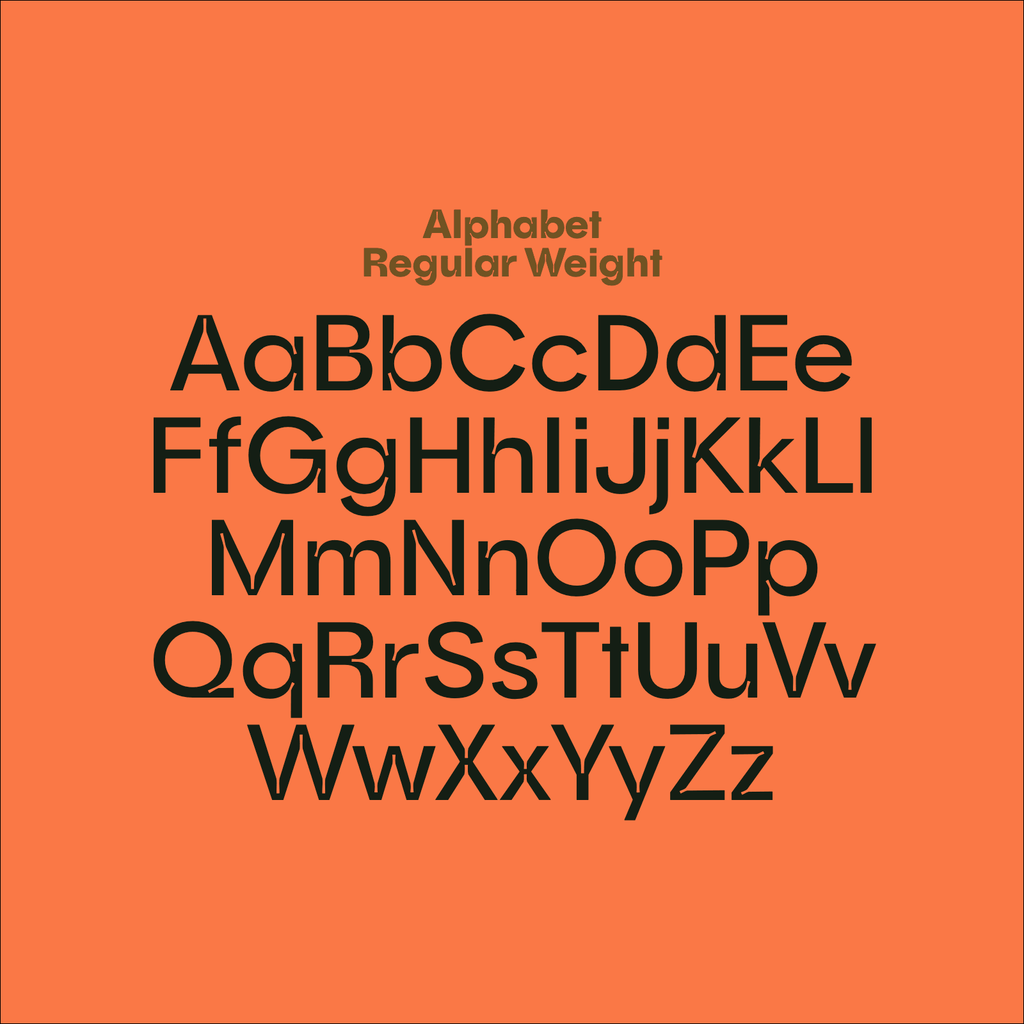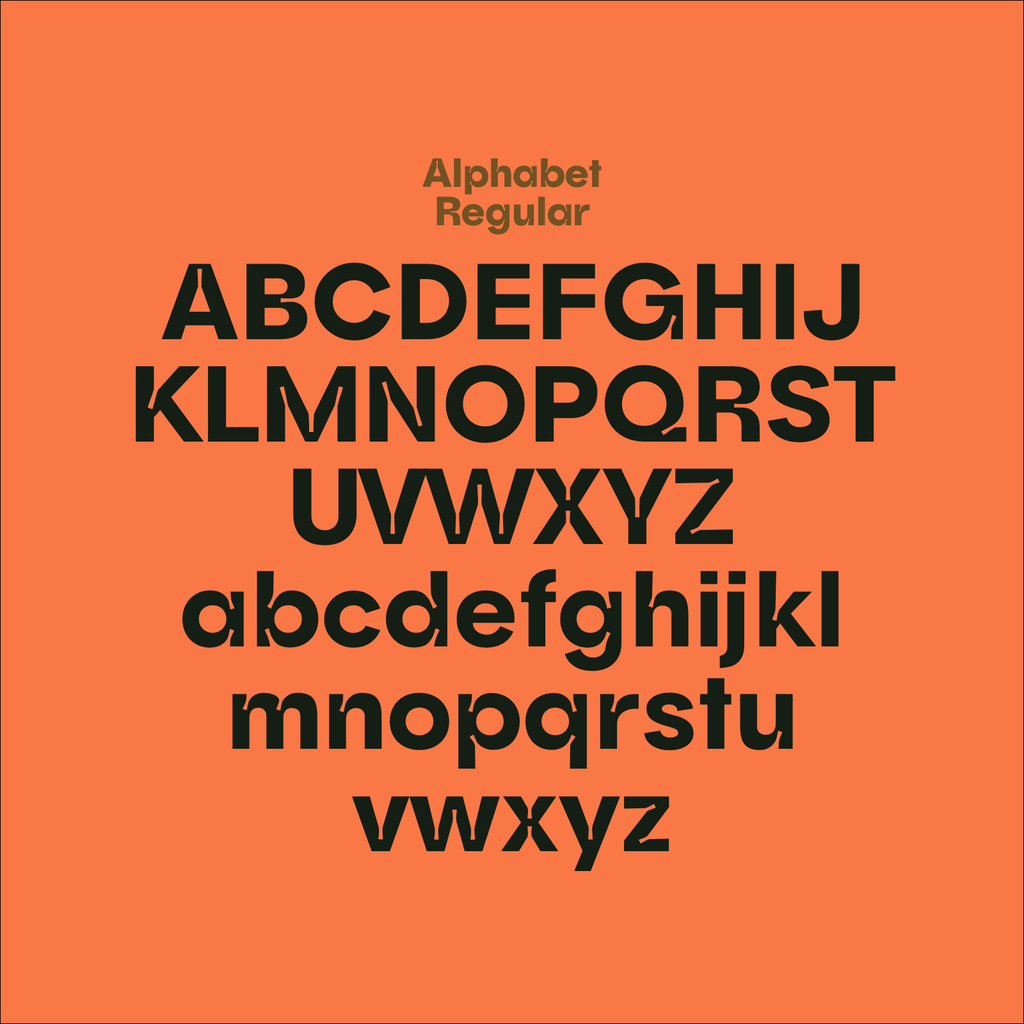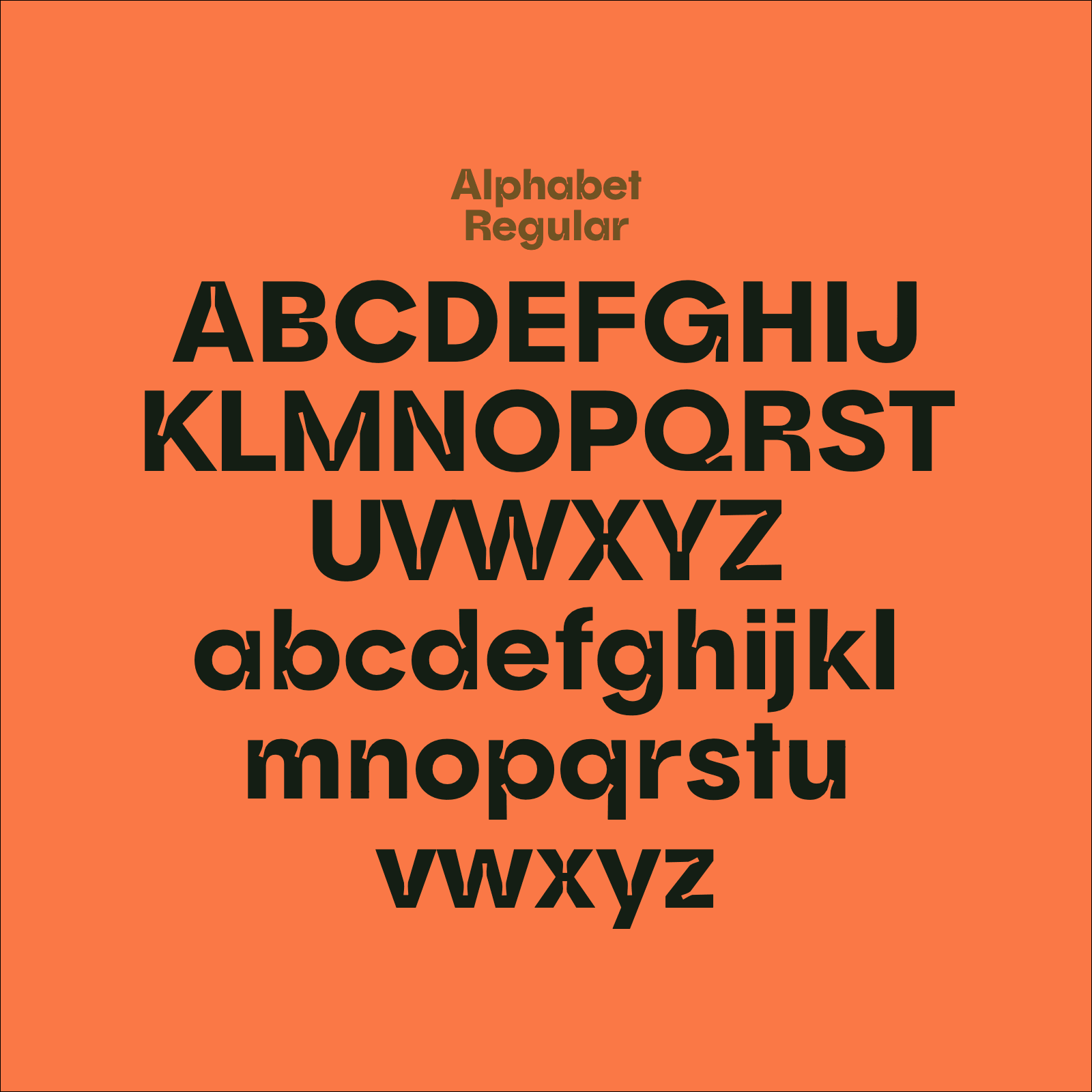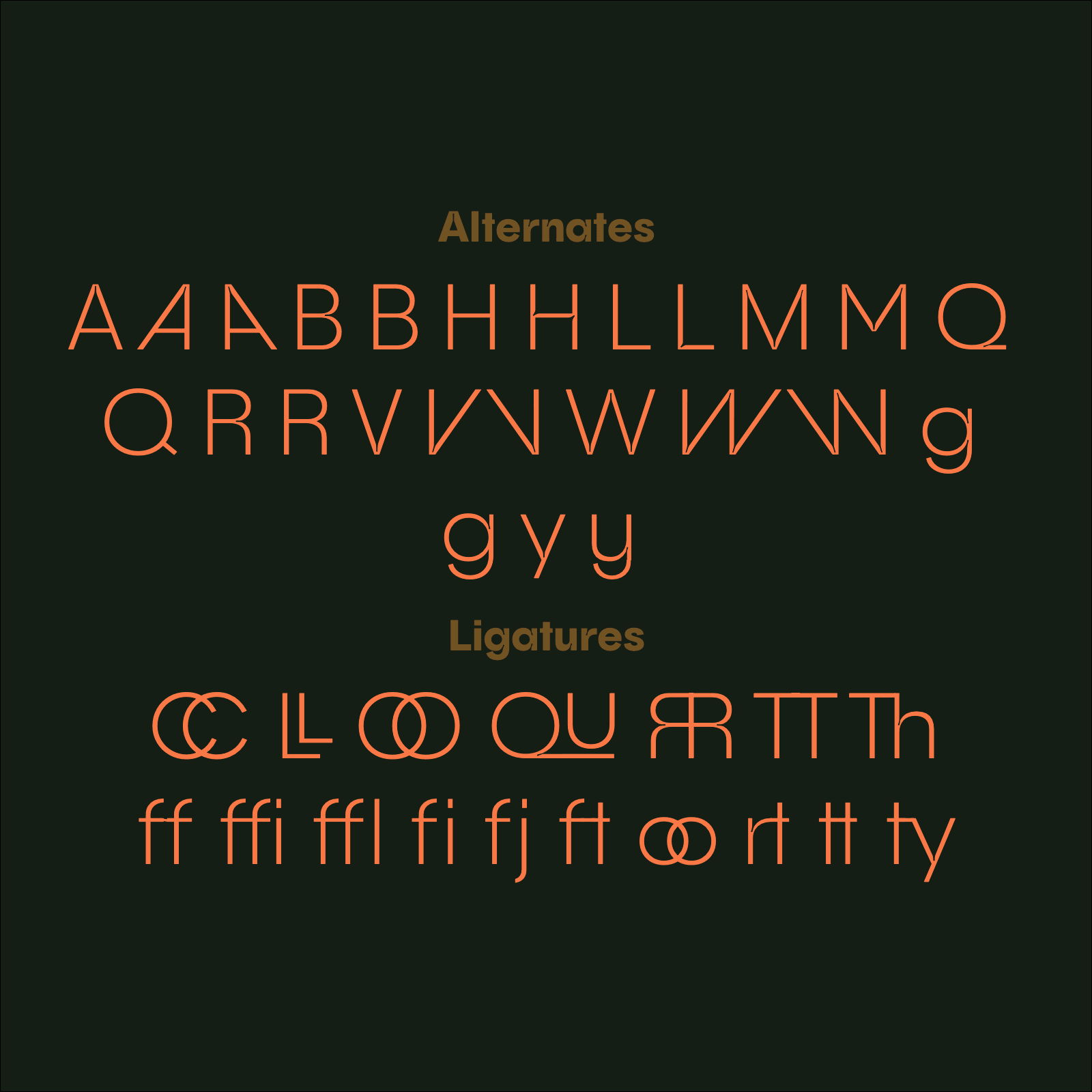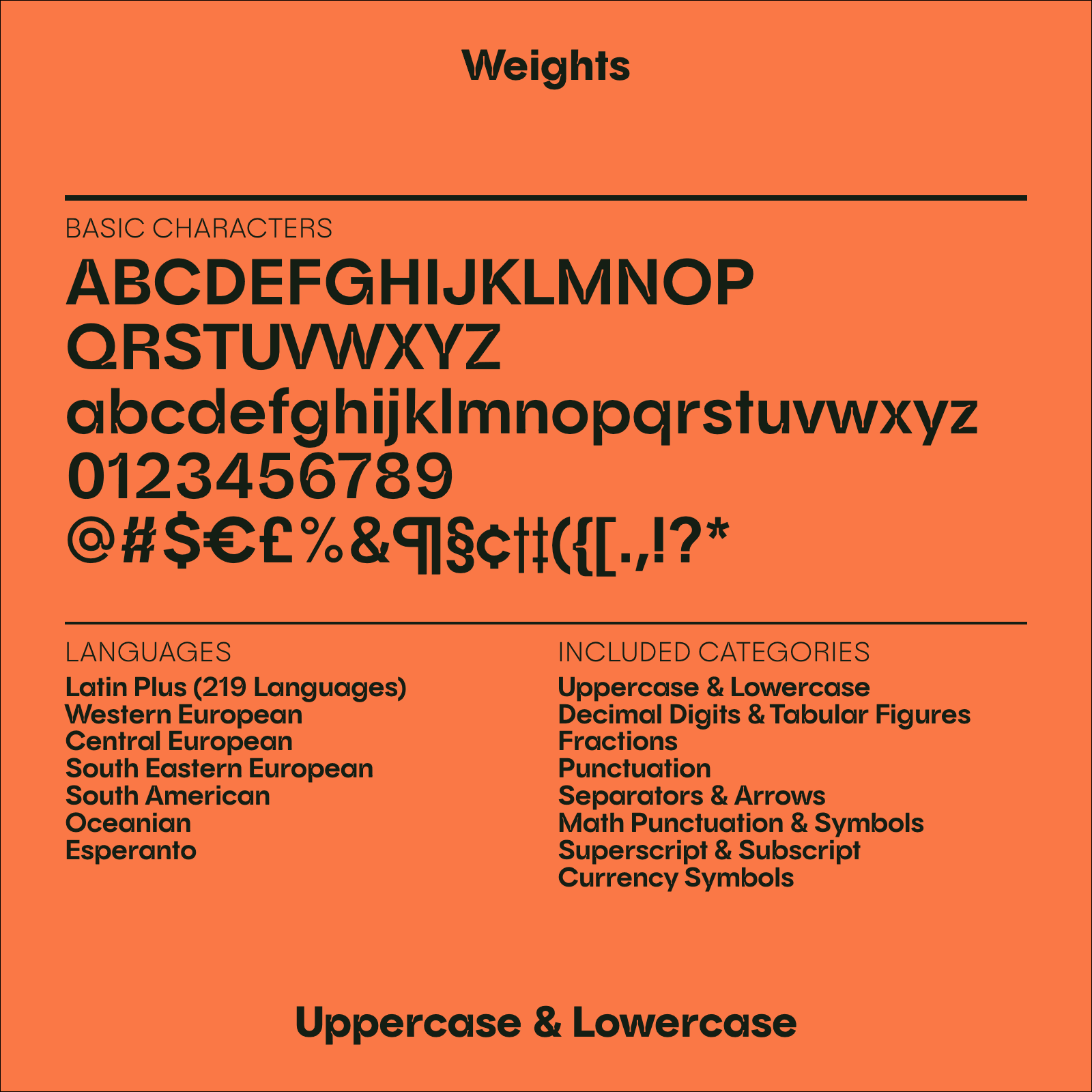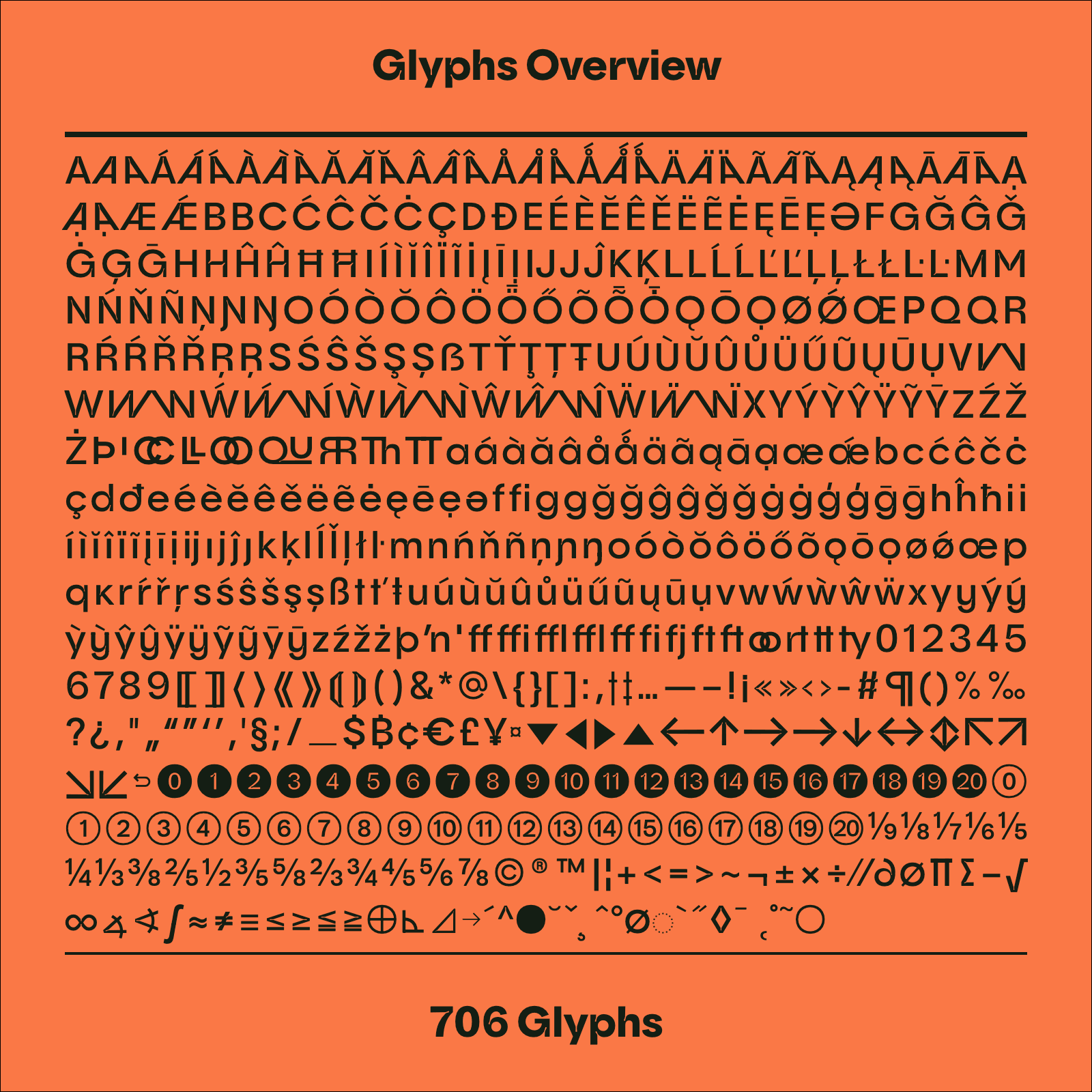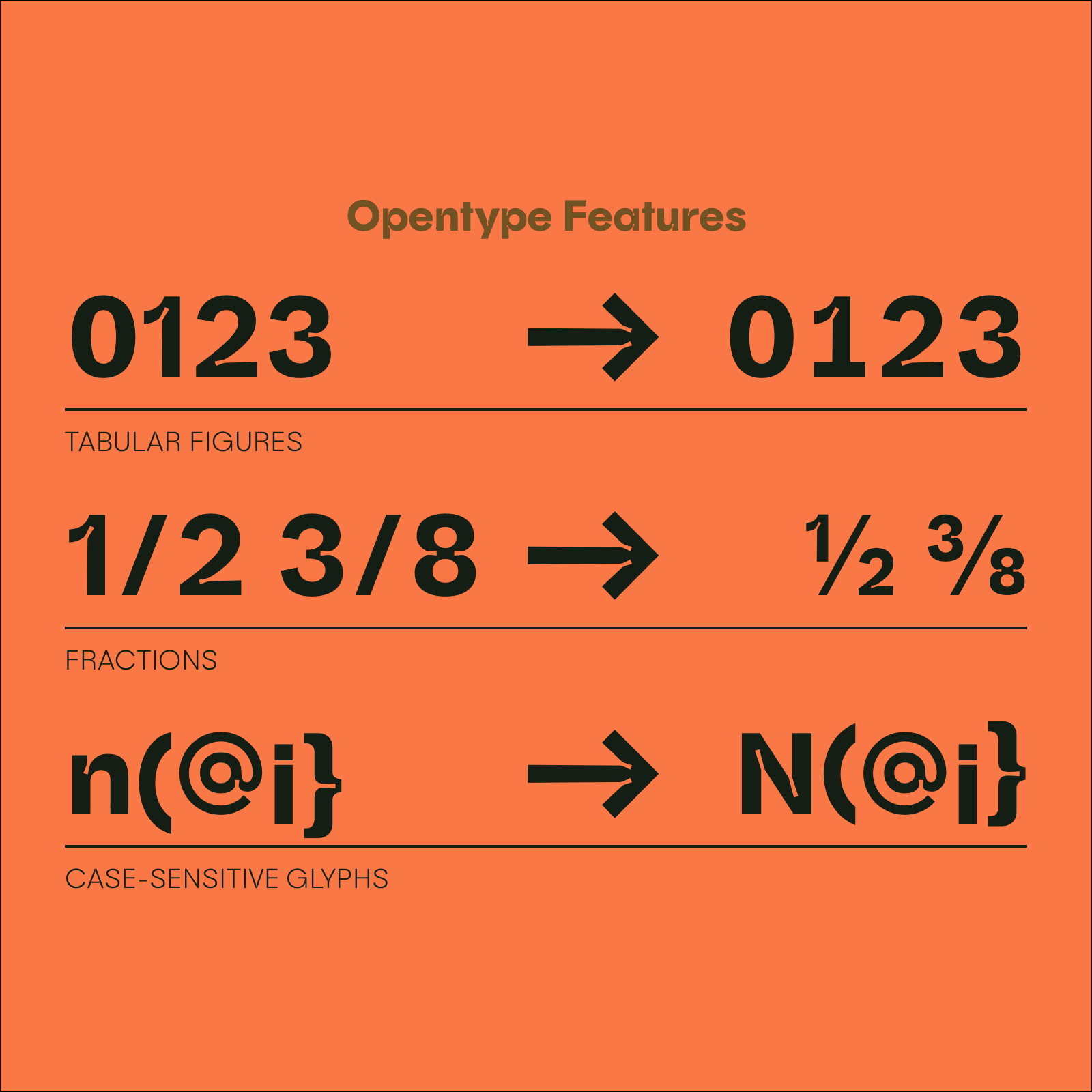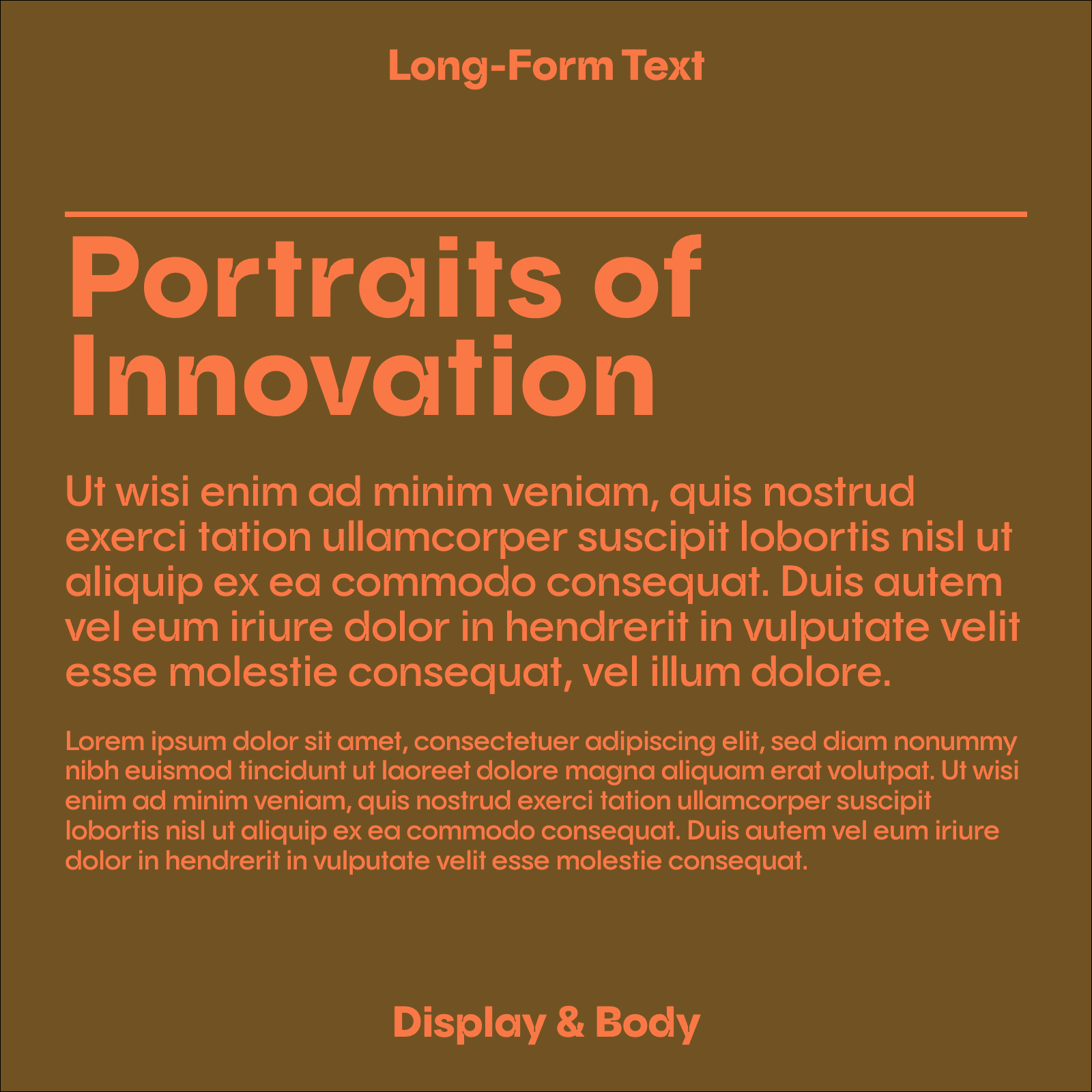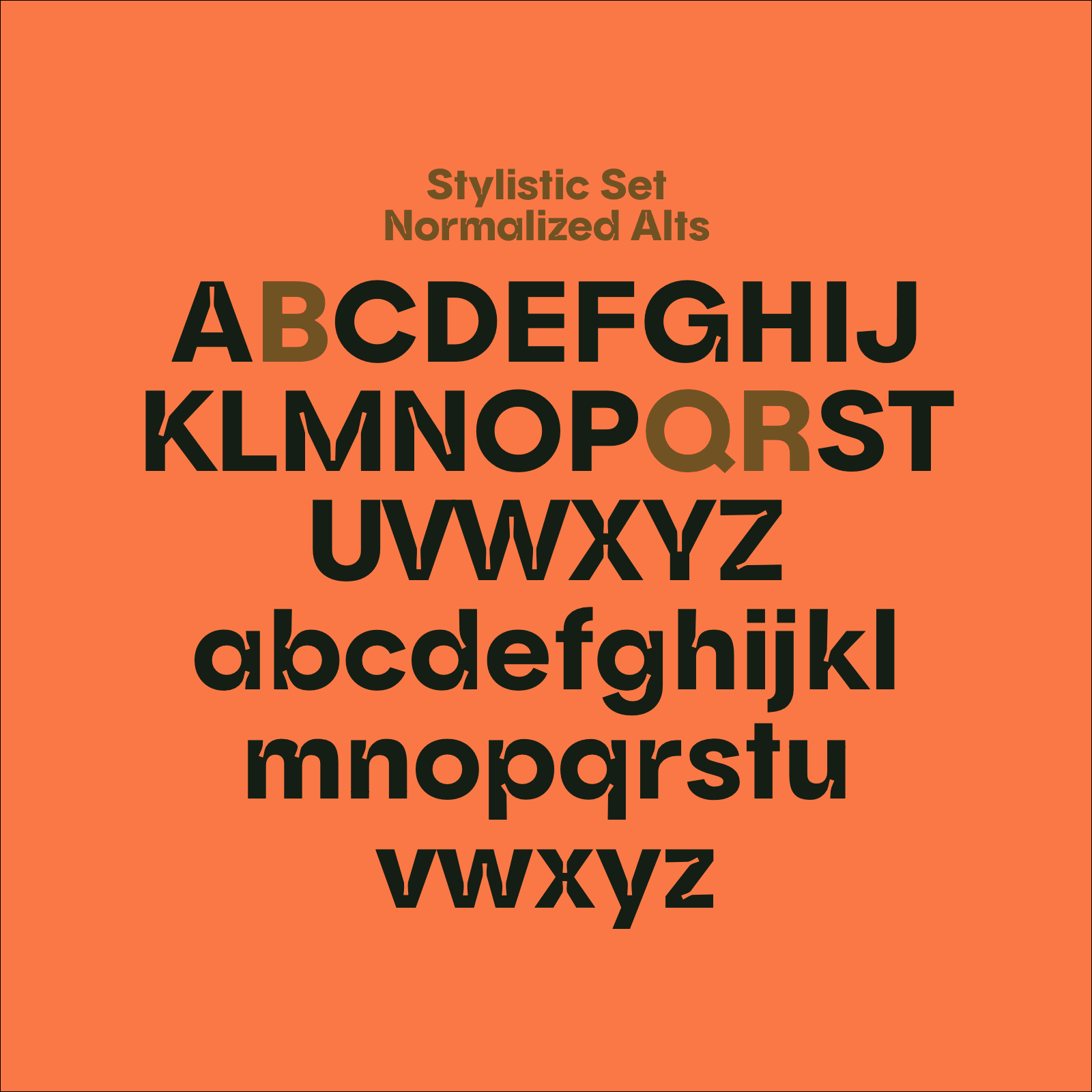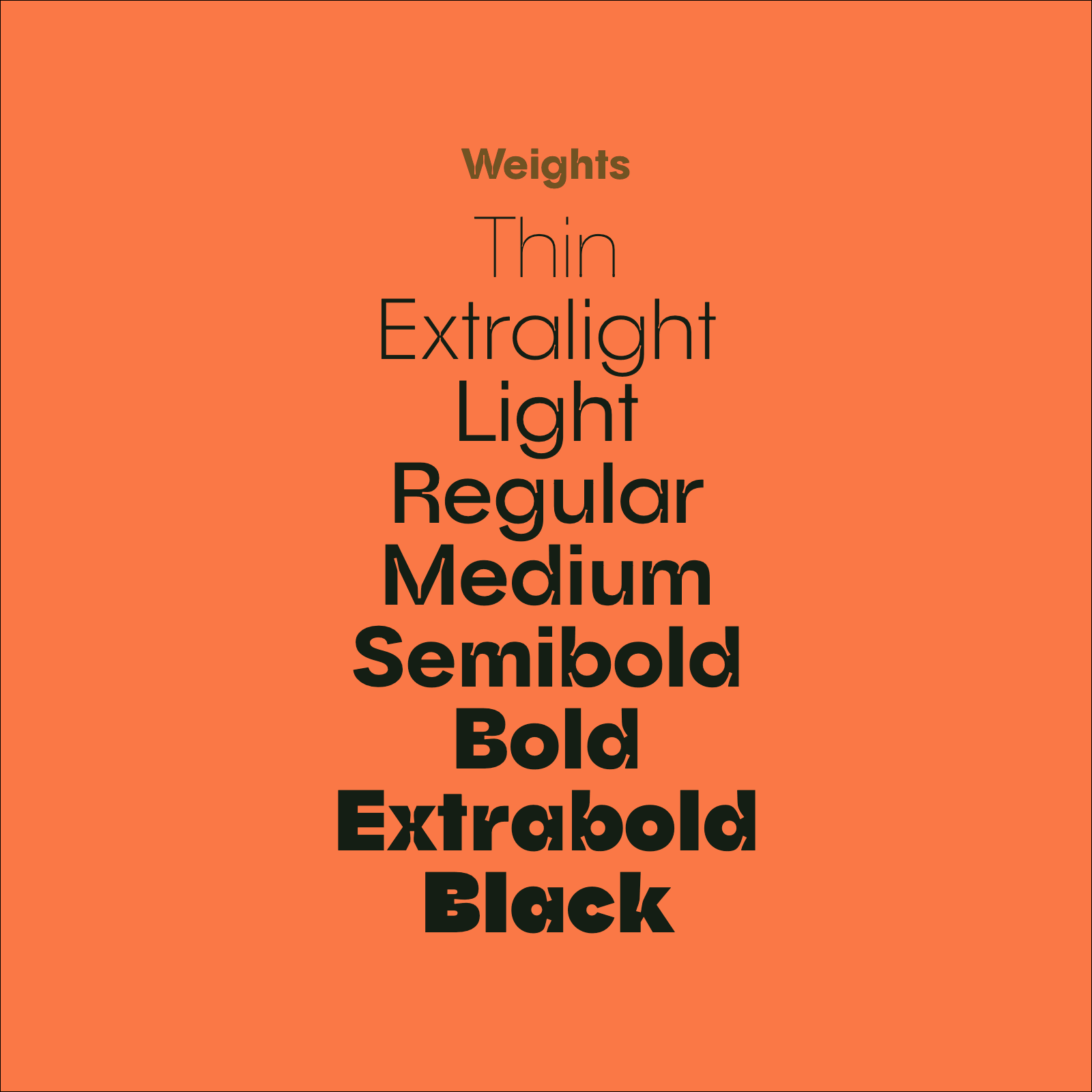
Kayon, geometric tech font shown as a brand overview
Kayon, Fuente Geométrica Tecnológica para Gaming y Branding
Kayon es una fuente tecnológica geométrica con raíces en la construcción, la arquitectura y la automatización. Sus trampas de tinta largas y angulares se estrechan en los puntos de unión de los trazos, lo que favorece la legibilidad en textos más largos. El diseño presenta una estructura robótica alineada con el branding de gaming y tecnología. Funciona bien para logotipos, títulos y composiciones editoriales. Está disponible en nueve pesos individuales y como familia completa con glifos alternativos. La familia completa incluye una fuente variable.
Kayon in detail
Family
Variable font, weight axis wght 100-950, with 9 named weights: Thin, ExtraLight, Light, Regular, Medium, SemiBold, Bold, ExtraBold, Black. 727 glyphs, 533 characters, 6 stylistic sets.
Languages
Latin, Western European accents, Central European.
Figures
Proportional, tabular, slashed zero.
OpenType features
Case-sensitive punctuation, discretionary ligatures, fractions, standard ligatures, proportional figures, tabular figures, slashed zero.
Ligatures
On by default: ff, fi, ffi, ffl, tt. Discretionary, switched on by the designer: fj, ft, ty, Th, TT, oo, OO, QU, RR, LL, rt.